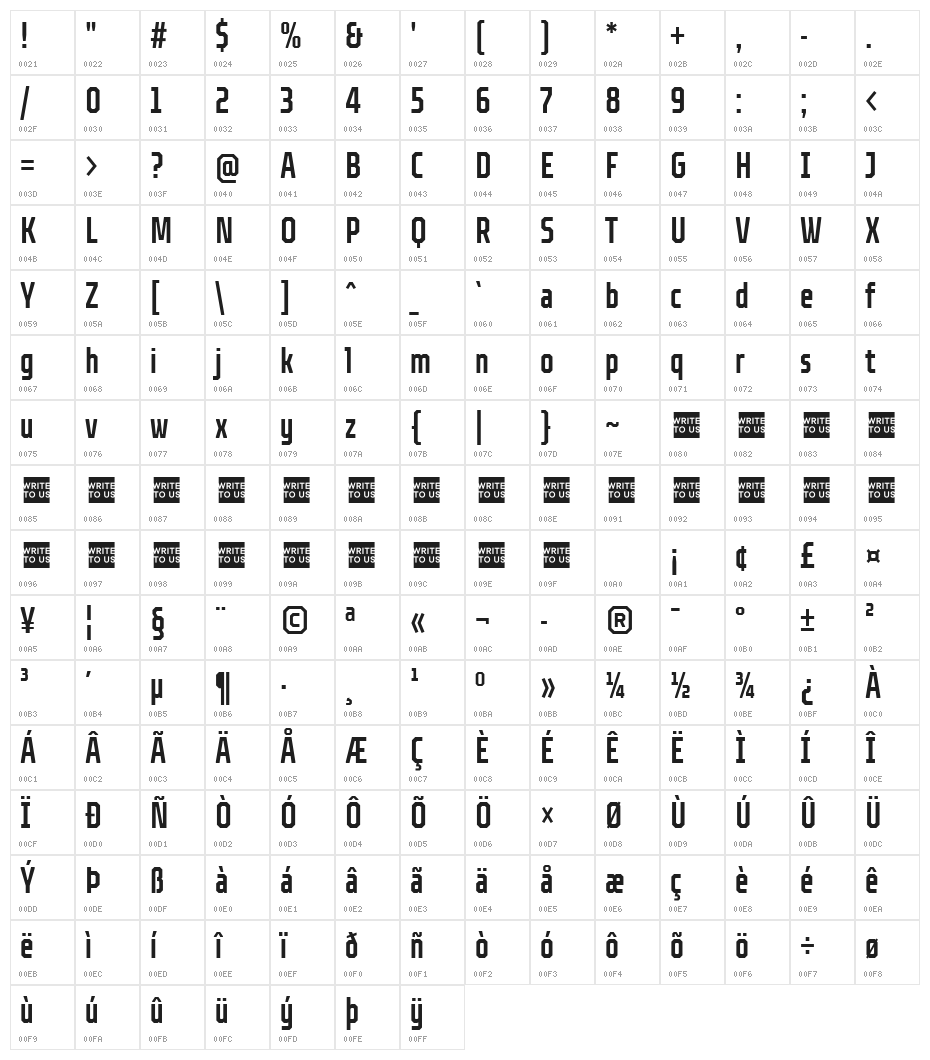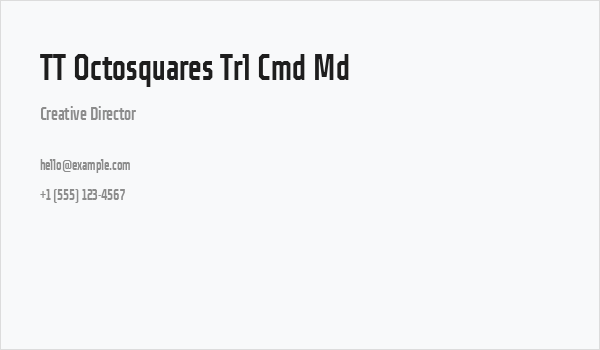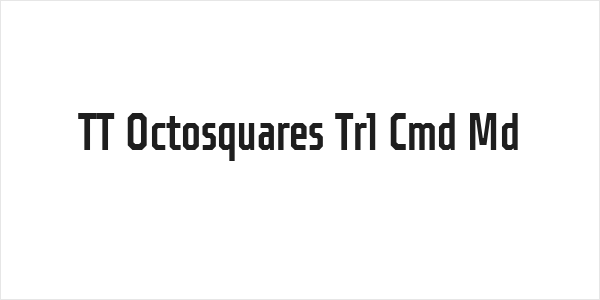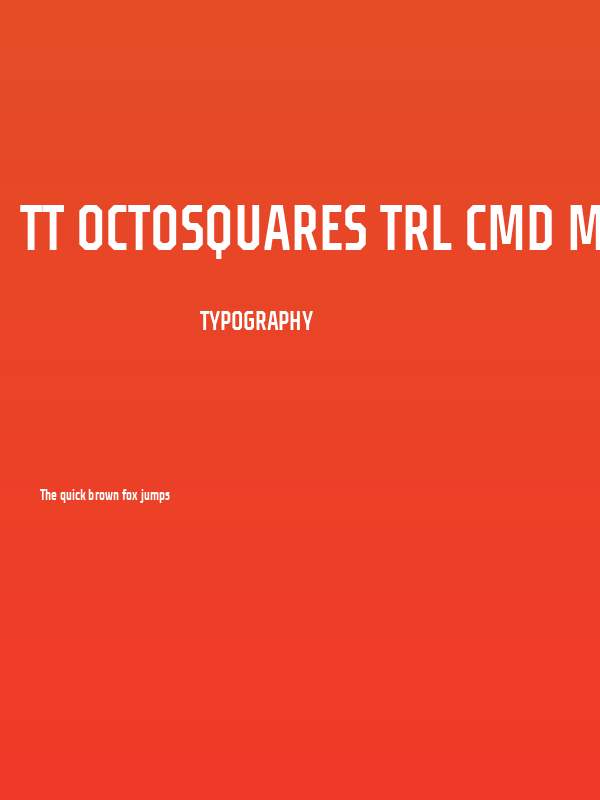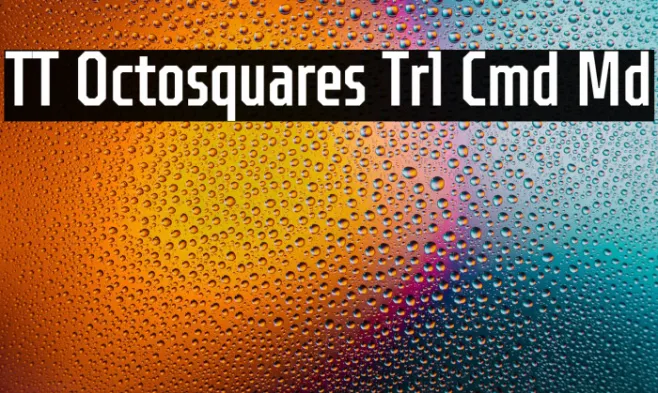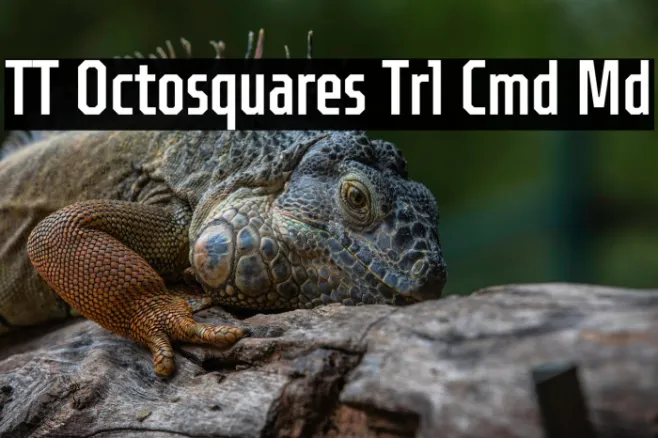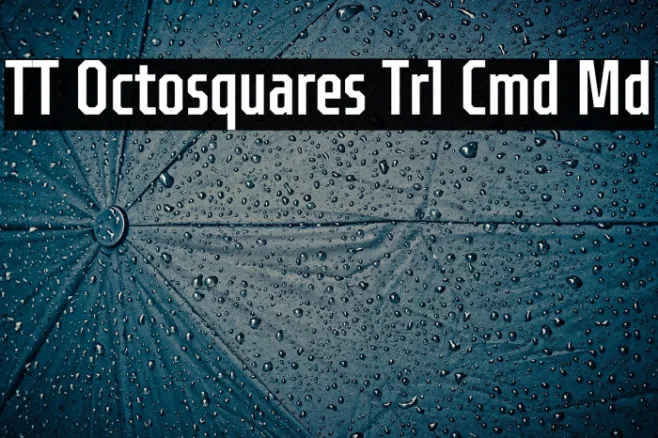
TT Octosquares Trl Cmd Md Font
| Vorgeschlagene Projekte | Ideal for branding, posters, headlines, and any design that requires a strong, modern look. |